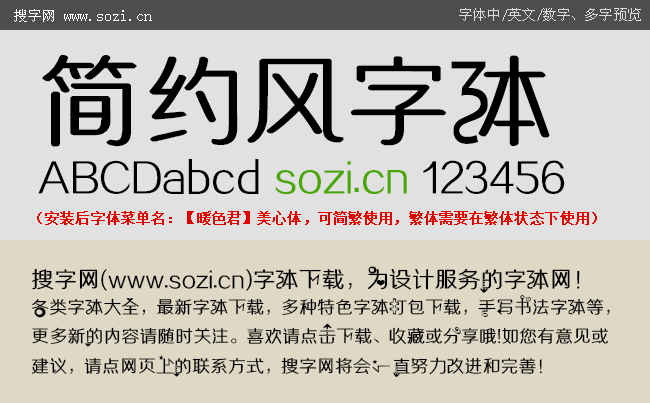
簡(jiǎn)約風(fēng)字體
搜字網(wǎng)給大家提供一款簡(jiǎn)約風(fēng)字體字體字體手機(jī)中文字體下載。這款手機(jī)字體是以正黑字體為原形。正黑體取傳統(tǒng)黑體結(jié)構(gòu),筆形全部采用平行、垂直與弧度的流線形設(shè)計(jì),簡(jiǎn)潔易識(shí)、美觀大方,具有個(gè)性,加之鏡像對(duì)稱的現(xiàn)代構(gòu)成形式,達(dá)到莊重與簡(jiǎn)潔有機(jī)融合、設(shè)計(jì)感與閱讀功能兼?zhèn)涞淖罱K效果。加入卡通裝飾后看上去非?蓯(ài),趣味實(shí)足。特別適合喜歡卡通的朋友在手機(jī)上安裝使用。